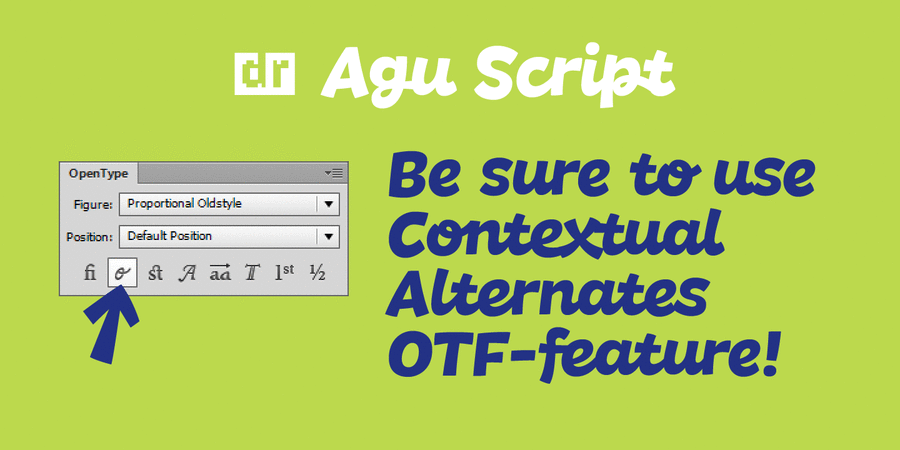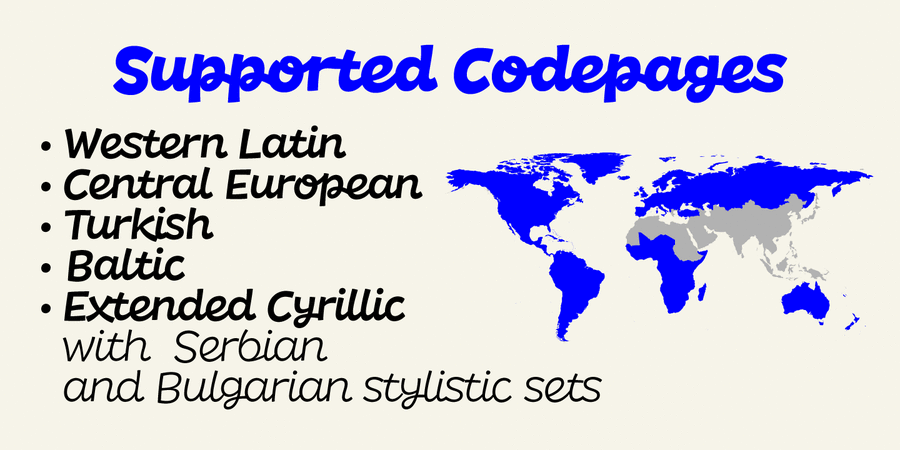
Опис гарнітури DR Agu ScriptШрифт Агу Скрипт – это семейство с набором из девяти курсивных начертаний от сверхсветлого до сверхжирного. Может применяться для неформальных текстов, детских книжек и приложений. Шрифт разработан Дмитрием Растворцевым в 2016 году.
Асоціації з сімейством шрифтів DR Agu ScriptОсобистість і характер гарнітури:
веселий, задерикуватий, смішний, доброзичливий, добродушний, добрий, радісний, стрибучий, неохайний, грайливий, привітний, пустотливий, непосидючий, рухливий, оригінальний, свіжий, тонкий, легкий, дитячий, наївний, невагомий, прозорий, ніжний, повітряний, дротяний, динамічний, худий, щасливий, літній, прикольний, карикатурний, милий, мультяшний, дотепний, домашній, симпатичний, стиглий, смачний, важкий, помітний, яскравий, новорічний, активний
дитяча книжка, канцтовари, олівці, зошит, анімація, мультфільм, АСМР, графіка, ілюстрація, школяр, ранок, гумор, море, селфі, Інстаграм, школа, табір, сніданок, іграшка, їжа, гра, канікули, учень, дитяче харчування, зоопарк, клоун, зоомагазин, тварини, відпочинок, щоденник, цирк, дім, закуска, розфарбування, піцца, базар, десерт, морозиво, смузі, Новий рік, дитсадок, дитячий ранок, Christmas Гарнітура асоціюється з віком: